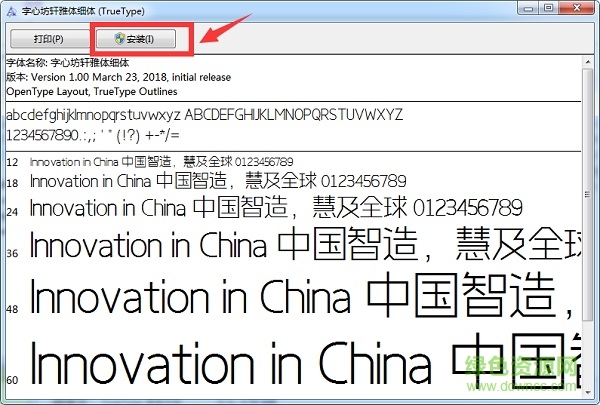
字心坊軒雅細體是字心坊軒雅字體系列的纖細字體,筆畫更加細長,字跡更加端方正直,給人比較大方得體的設計好感,快來綠色資源網(wǎng)試試吧!
該字體為字心坊軒雅體字體系列作品的纖細款字型字體。字體采用非襯線設計,全部筆畫采用直線設計。字體個性鮮明,字形特點時尚新穎,同時融入古風結構,靈活多變的線條造就此款字體的與眾不同。
該宇體采用非襯線設計,全部筆畫采用直線設計。宇體個性鮮明,宇形特點時尚新穎,同時融入古風結構,靈活多變的線條造就此款宇體的與眾不同。宇體風格新穎、時尚。